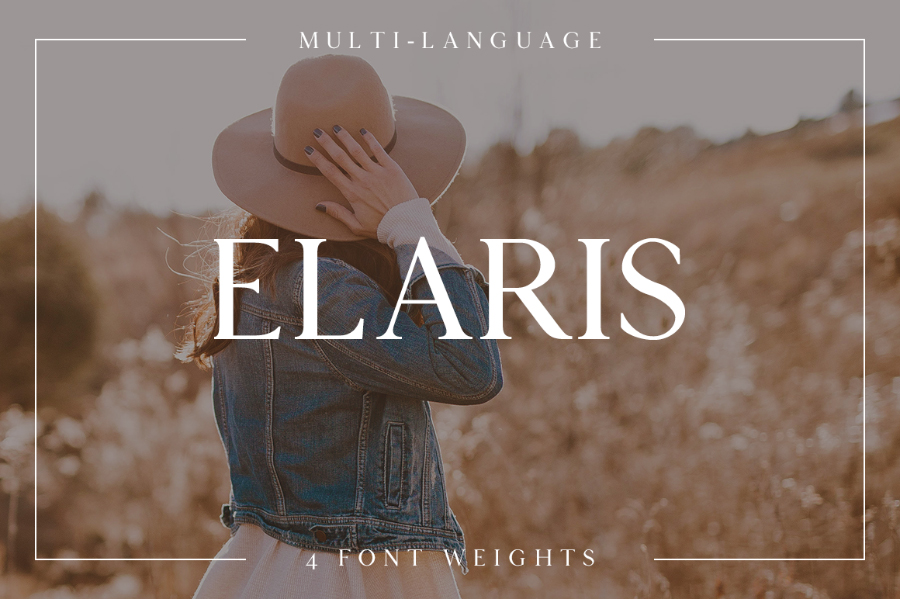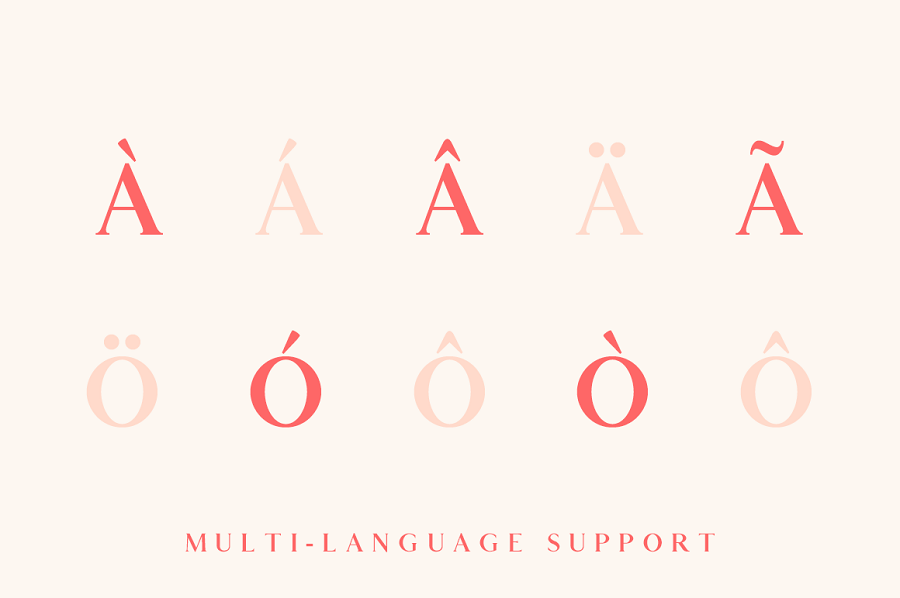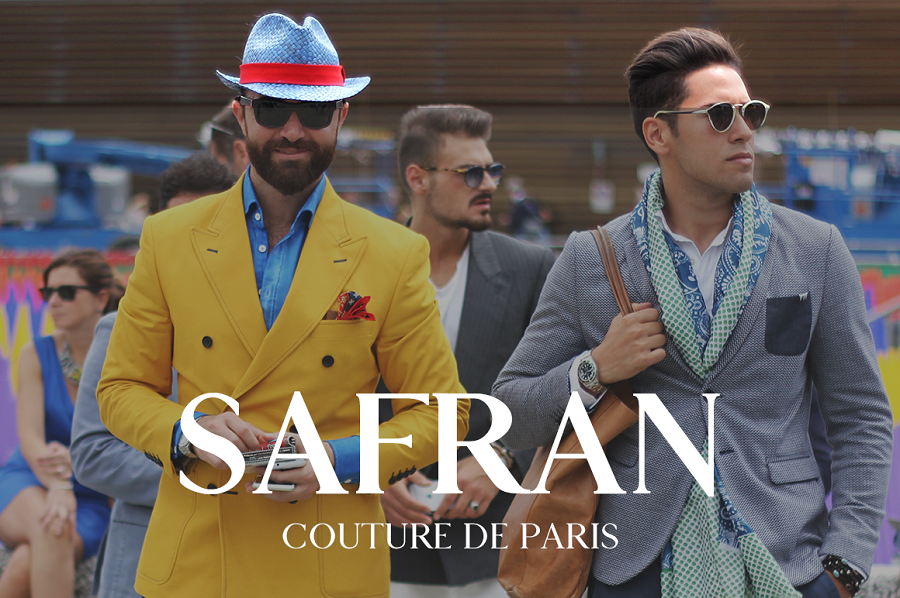
Elaris Serif免费字体
Elaris Serif免费字体是一个潇洒,高级的衬线字体。具有流动的字母,广泛的语言支持和大量的字符,Elaris是标题,标题和标志的完美字体。这种字体是对过去的印刷传统的赞扬,并且迈出了一个更加美好,更加美好的未来。所以,今天你可以有Elaris Regular的免费演示!